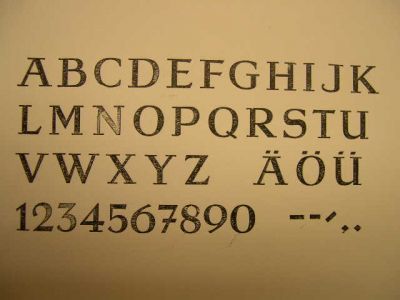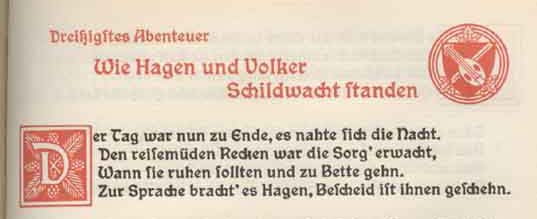
Deutsche Reichsdruckerei Berlin - welche Schrift ist das?
diese Versal-Schrift stammt von der Reichsdruckerei Berlin. Alle Lettern verfügen über eine Gußmarke mit dem Reichsadler. Sie stammt, geschätzt, aus der Zeit um 1920.
Wer kann mir sagen, wie diese Schrift heißt?
Die Reichsdruckerei hat damals exklusiv für sich arbeiten lassen.
Ich habe mal in der Bibliothek des Klingspormuseums wegen einer Sattler-Schrift nachgefragt. Die haben mir freundlicherweise eine Seite aus einer Festschrift über die Reichsdruckerei mit der Seitenzahl 239 kopiert. Dort sind Typen aufgelistet, die für die Reichsdruckerei geschnitten wurden.
Leider fehlt das gezeigt Muster, trotzdem will ich an dieser Stelle mal die Namen in Netz geben.
Schriften der Reichsdruckerei (unvollständig):
1897 Nibelungenschrift (von Sattler)
1899 Neudeutsch
1899 Breite Voigtsche Gotisch
1900 Borussia
1900 Germania
1900 Magere Voigtsche Gotisch
1900 Schmale Voigtsche Gotisch
1905 Reichsdruckerei Fraktur
1905 Reichsdruckerei Mediäval
1917 Huppschrift (von Otto Hupp warscheinlich)
1928 Reichsdruckerei Schwabacher
1928 Reichsdruckerei Gotisch
Ästhetisch sind das alles keine dollen Typen... aber bestimmt sehr exklusiv und nur in gewissen Graden bzw. Größen geschnitten.
Es würde mich wundern, wenn die Reichsdruckerei ihre Typen auf dem freien Markt angeboten hätte, somit sind das sicherlich sehr, sehr seltene Typen - also etwas fürs Museum.
Ich habe gestern bei zvab das Nibelungenlied, gesetzt aus der Germania, gekauft. Wenn es ankommt und es sich lohnt, werde ich hier mal ein paar Muster einstellen.
Was die Ästhetik betrifft:
Kann man denn wirklich mit unserer heutigen Sicht Ästhetik einer Epoche bewerten, die wir selbst gar nicht erlebt haben?
Ich meine die Frage nicht rhetorisch. Was empfinden wir denn als Ästhetik? Das ist doch irgendwo die Summe aus sozialem Hintergrund, erfahrener Kultur und Seh-Gewohnheit. Und das gilt doch für das Ästhetik-Empfinden der Menschen früherer Epochen. Ich kann mir nicht vorstellen, daß eine Reichsdruckerei nicht wert auf Ästhetik gelegt hat - aus dem subjektiven Empfinden der damals Verantwortlichen.
Wenn wir nun aus heutiger Sicht eine alte Schrift als ästhetisch empfinden - ist es dann nicht sehr oft einfach so, daß sich unsere Summe ästhetischer Werte mit der Summe der damals vorhandenen ästhetischen Werten überschneidet? Mehr oder weniger zufällig?
Oder ist Ästhetik zeitlos?
Zweifellos gibt es ja Schriften, die epoche-übergreifend als ästhetisch empfunden werden. Die man also als "zeitlos" bezeichnen kann.
ich denke schon dass unser ästhetische empfinden durch unsere sozialisierung zeitlich geprägt ist. für die bewertung von schriften muss das aber, denke ich, reichen. ich mag keine mönchshandschriften aus dem 11jhr. in einem buch lesen müssen - nur weil das mal jemand schön fand, muss ich es ja nicht schön finden.
verstehst du was ich meine? wohl fanden die verantwortlichen damals die schriften schön oder interessant - aber das muss ich heute ja nicht gleich sehen.
Das ist genau, was ich meine.
Nur hast Du es wesentlich kürzer und prägnanter ausgedrückt.
Andreass schrieb "Ästhetisch sind das alles keine dollen Typen... "
Ich versuche oft, mich beim Einschätzen von Schriften vom Standpunkt eines damaligen Betrachters zu nähern. Deshalb habe ich auch einmal die Block aus dem Jahre 1903 als sensationell bezeichnet:
Oder auch die Bigband aus dem Jahr 1974 als ihrer Zeit voraus:
Eben weil diese Schriften aus Sicht der damaligen Betrachter eine Provokation gewesen sein müssen. Allein schon die Bezeichnung "grotesk" für Schriften, die es heute schwer haben, das Image eines Langweilers zu umgehen, zeigt doch, daß das Empfinden der Menschen ein völlig anderes war. Und genau das ist es, was mir hilft, diese Epochen zu verstehen.
Ein Urteil "ästhetisch" oder nicht erlaube ich mir nur, wenn ich meine, so etwas am Maßstab der jeweiligen Epoche festmachen zu können. Also zum Beispiel im Vergleich zu anderen Schriften gleicher Art aus der gleichen Epoche.
Nochmal: Das soll kein Vorwurf sein. Nur eine Erklärung, wie ich selbst an diese Sache herangehe.
ist jetzt themenfremd, aber trotzdem interessant.
Eben weil diese Schriften aus Sicht der damaligen Betrachter eine Provokation gewesen sein müssen. Allein schon die Bezeichnung "grotesk" für Schriften, die es heute schwer haben, das Image eines Langweilers zu umgehen, zeigt doch, daß das Empfinden der Menschen ein völlig anderes war. Und genau das ist es, was mir hilft, diese Epochen zu verstehen.
diese erklärung wird übrigens nicht von allen geteilt. hier ein zitat von typophile.com:
"Grotesque" is used in the "primeval" sense of the word, from the Italian 'grottesco' ("of a grotto.") Grotesque types were so named at the beginning of the nineteenth century because of the vogue for antiquity -- the Napoleonic conquest of Egypt ended in these years, and the craze for antiquities led manufacturers of all sorts to attach ancient sounding names to anything novel. Different typefounders chose their own historical names for this new sans serif style, among them "Egyptian," "Doric," "Antique," and "Gothic." The last two terms live on to this day, e.g. "Franklin Gothic."
Du komprimierst Deine JPGs zu stark. Ich würde auch gern einmal eine komplette Seite sehen, bitte.
Ich probier's..